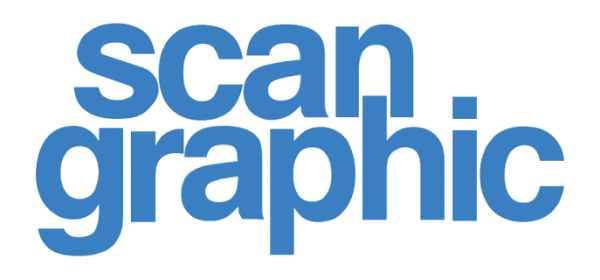
- Land: Deutschland
- Status: nicht mehr aktiv
Scangraphic war in den 1980er Jahren ein bekannter Hersteller von Satzmaschinen.
Die Scangraphic Digital Type Collection ist mittlerweile wieder über Elsner und Flake wieder in verschiedenen verfügbar.
Die Schriftenbibliothek umfaßt zur Zeit über 1000 verschiedene Schriftschnitte. Darunter befinden sich Schriftfamilien wie die Today Sans Serif von Volker Küster und die Zapf Renaissance Antiqua von Hermann Zapf. Einmaliges Merkmal dieser Schriften ist, dass von mehr als 60 Prozent der Schriftschnitte zwei Ausführungen zur Verfügung stehen, eine für Textsatz, die Bodytypes, und eine für den Titelsatz, die Supertypes. Scangraphic empfiehlt, die Bodytypes nicht größer und die Supertypes nicht kleiner als 4,5 mm Versalhöhe (18 Punkt) anzuwenden.